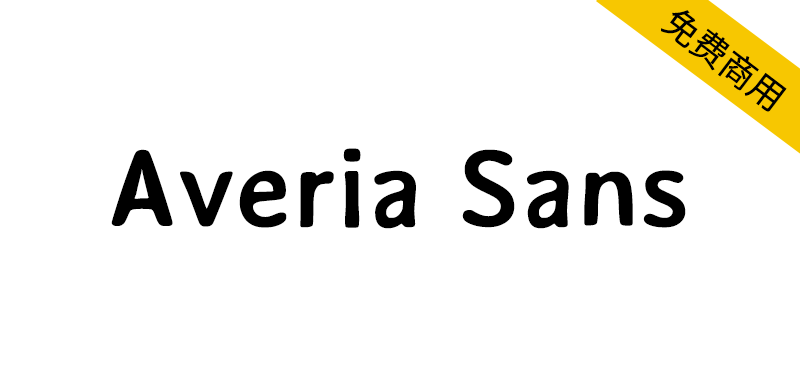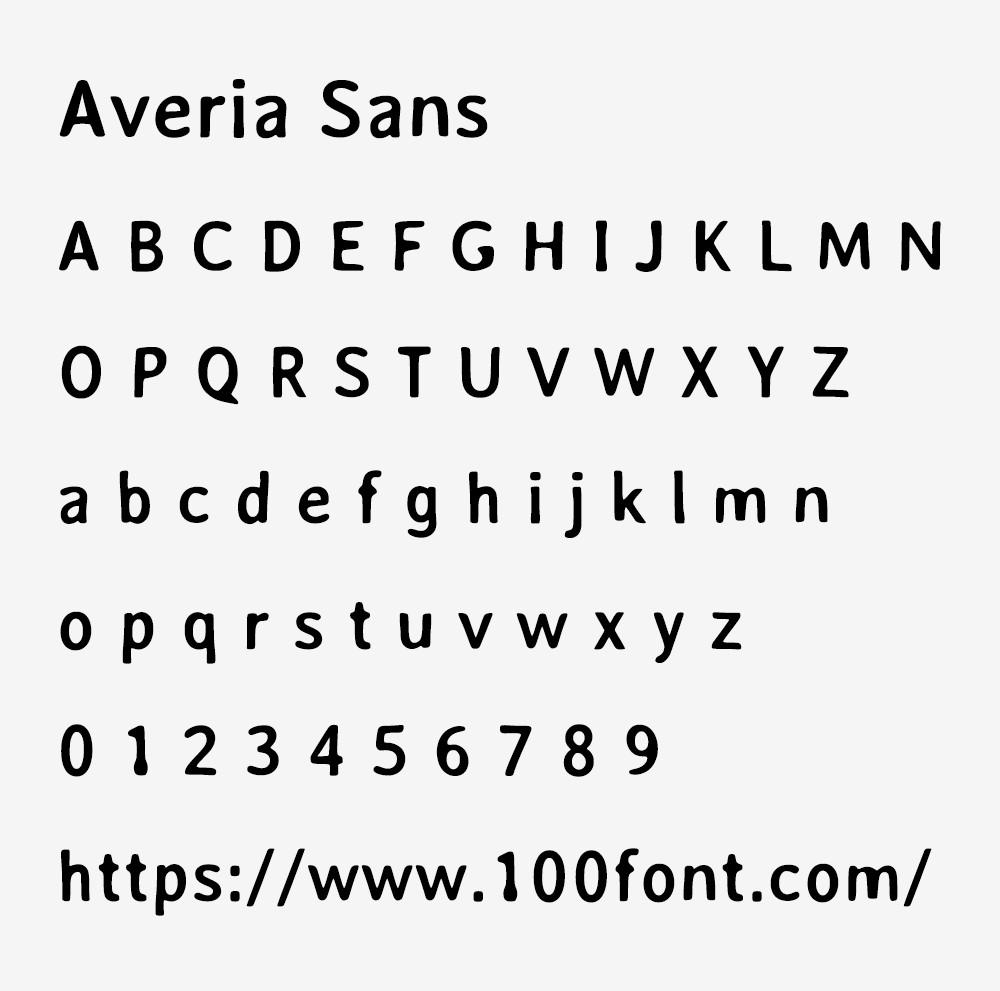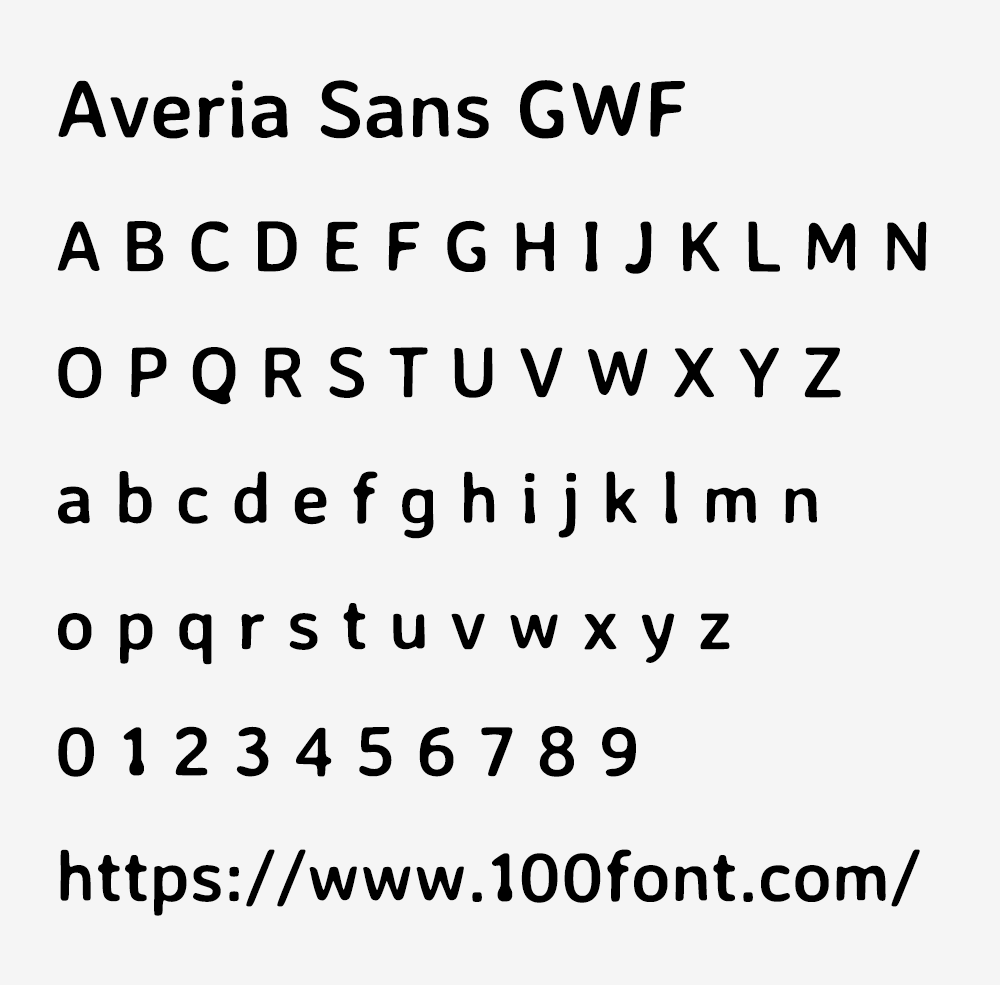
Averia Sans 是 Averia 字体家族中的无衬线(Sans Serif)版本,由设计师 Dan Sayers 创作。它继承了 Averia 系列标志性的“复古印刷”风格,但去除了衬线,呈现出更简洁、现代的外观,同时保留了轻微的手工质感。字形干净简洁,但笔画末端带有微妙的墨水晕染效果,模拟老式印刷的不完美感,比标准无衬线字体更有个性,适合创意设计。
Averia Sans GWF:是 Averia Sans字体的一个变体,专为网页优化设计。它保留了 Averia 系列标志性的“复古印刷”风格,同时针对屏幕显示进行了细节调整,确保在网页上具有良好的可读性和渲染效果。